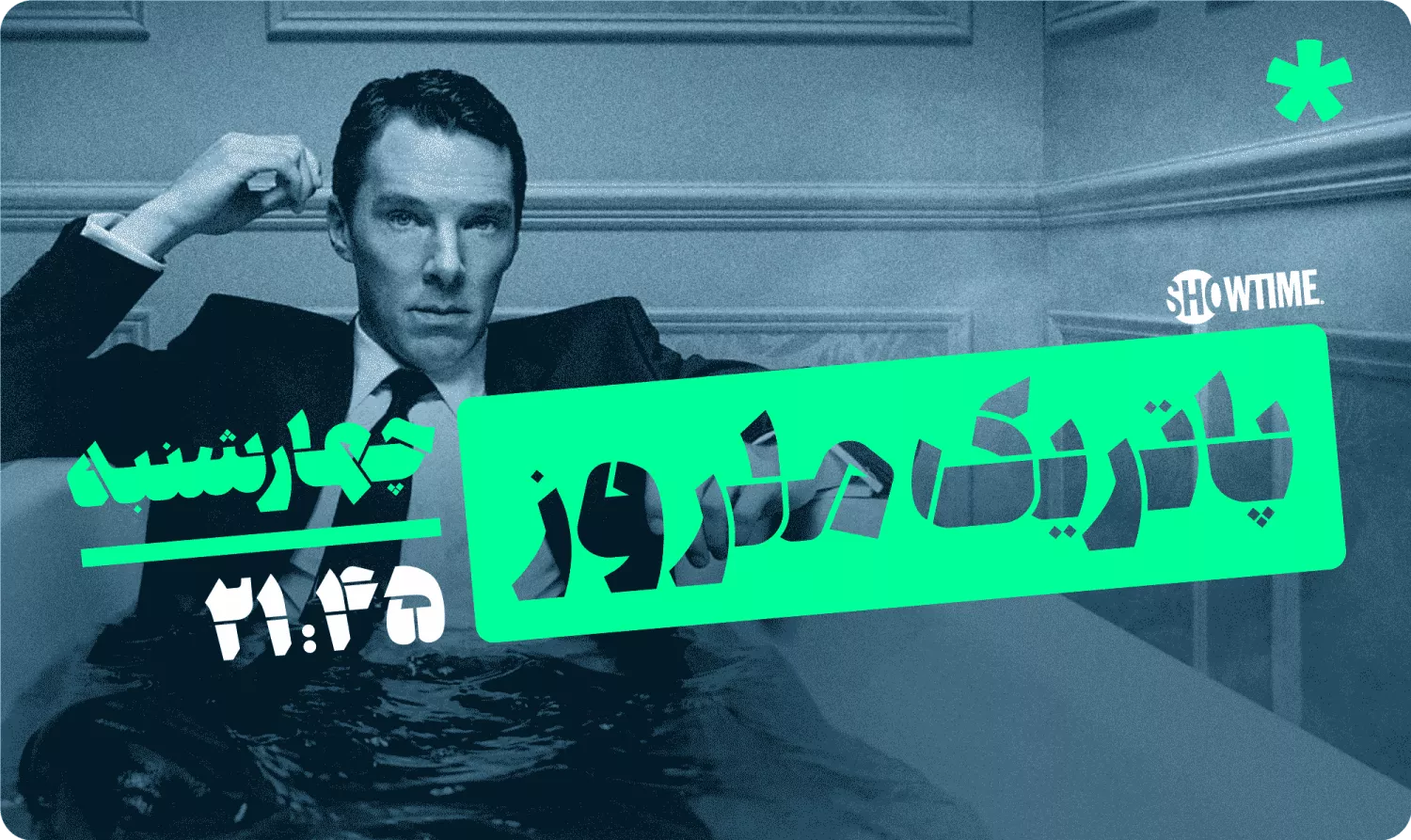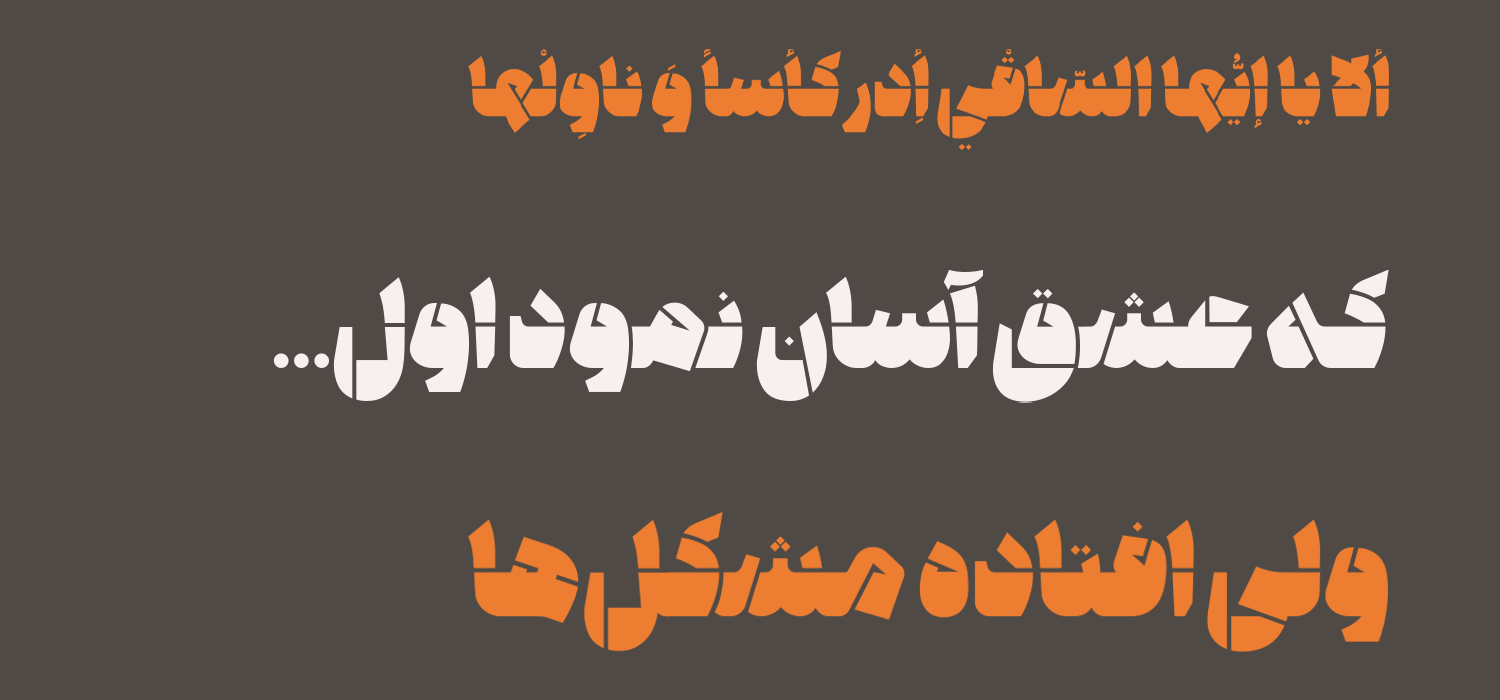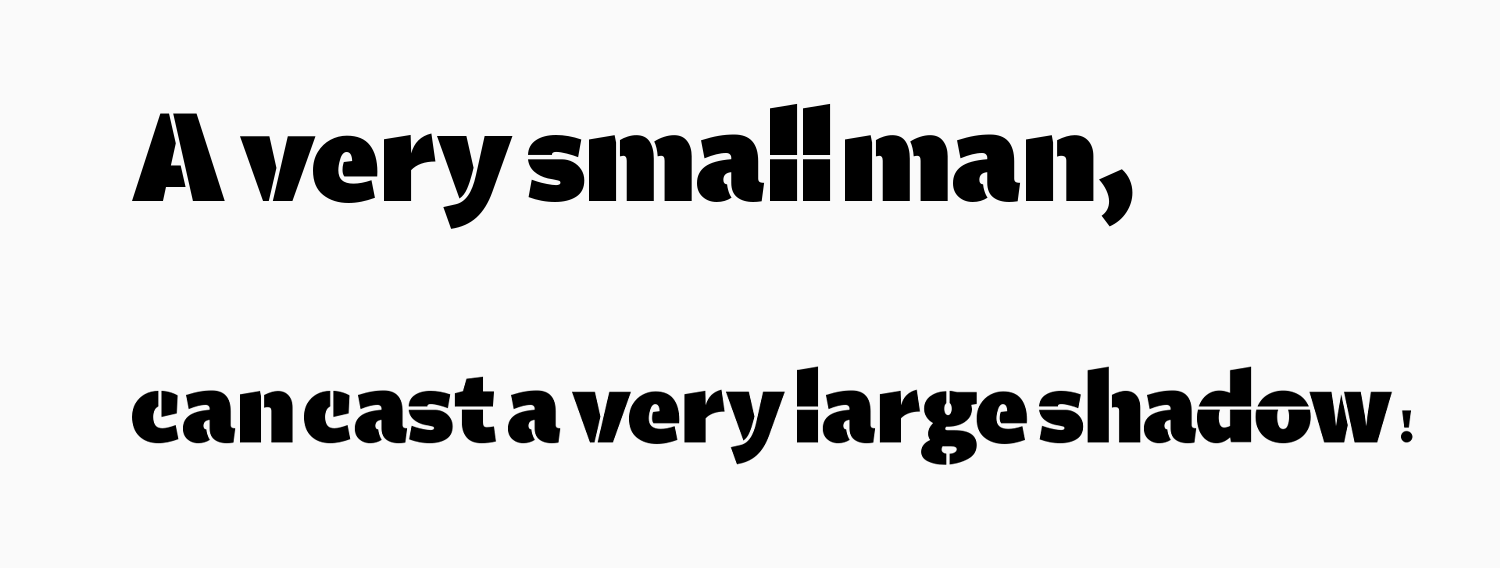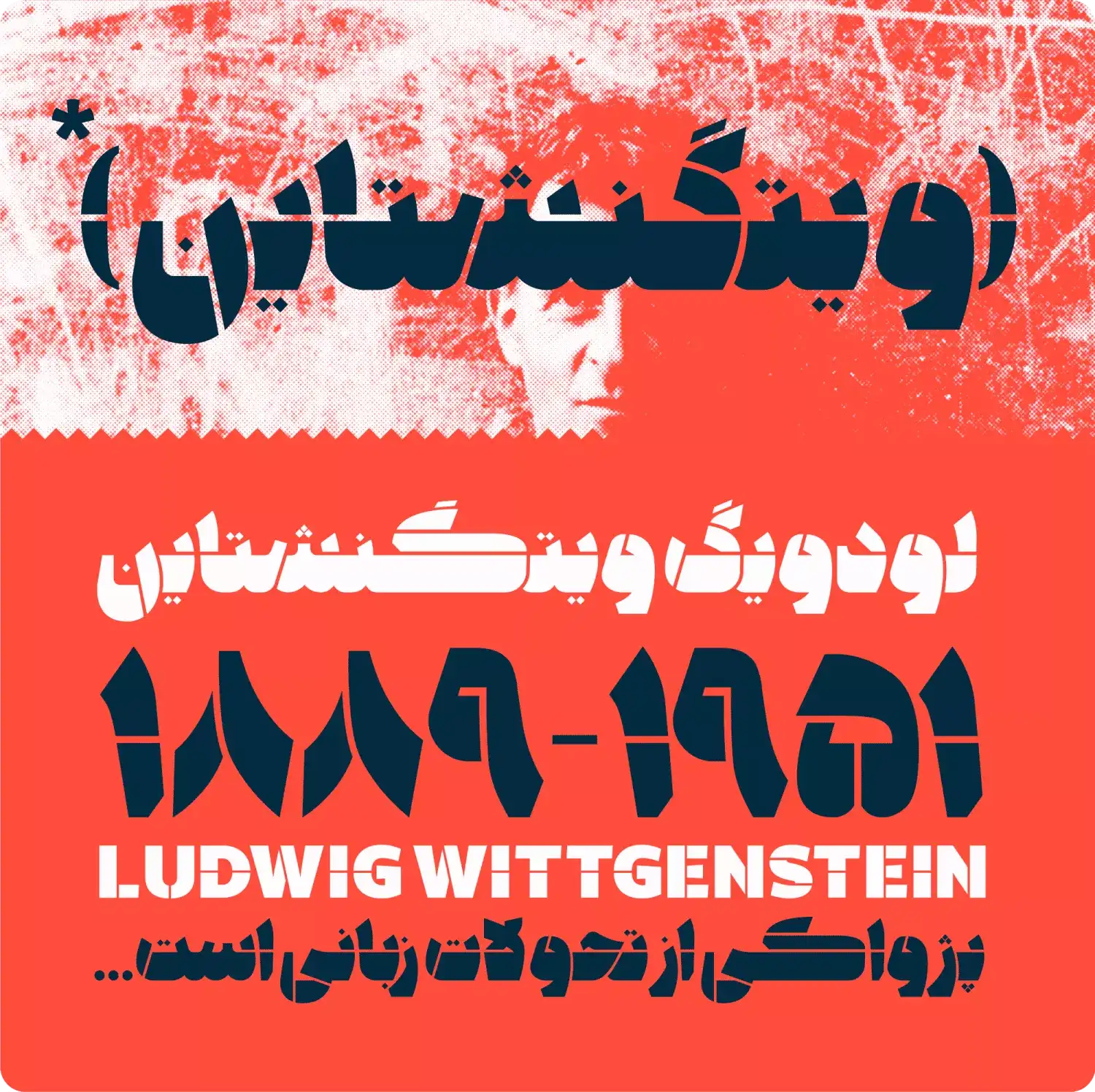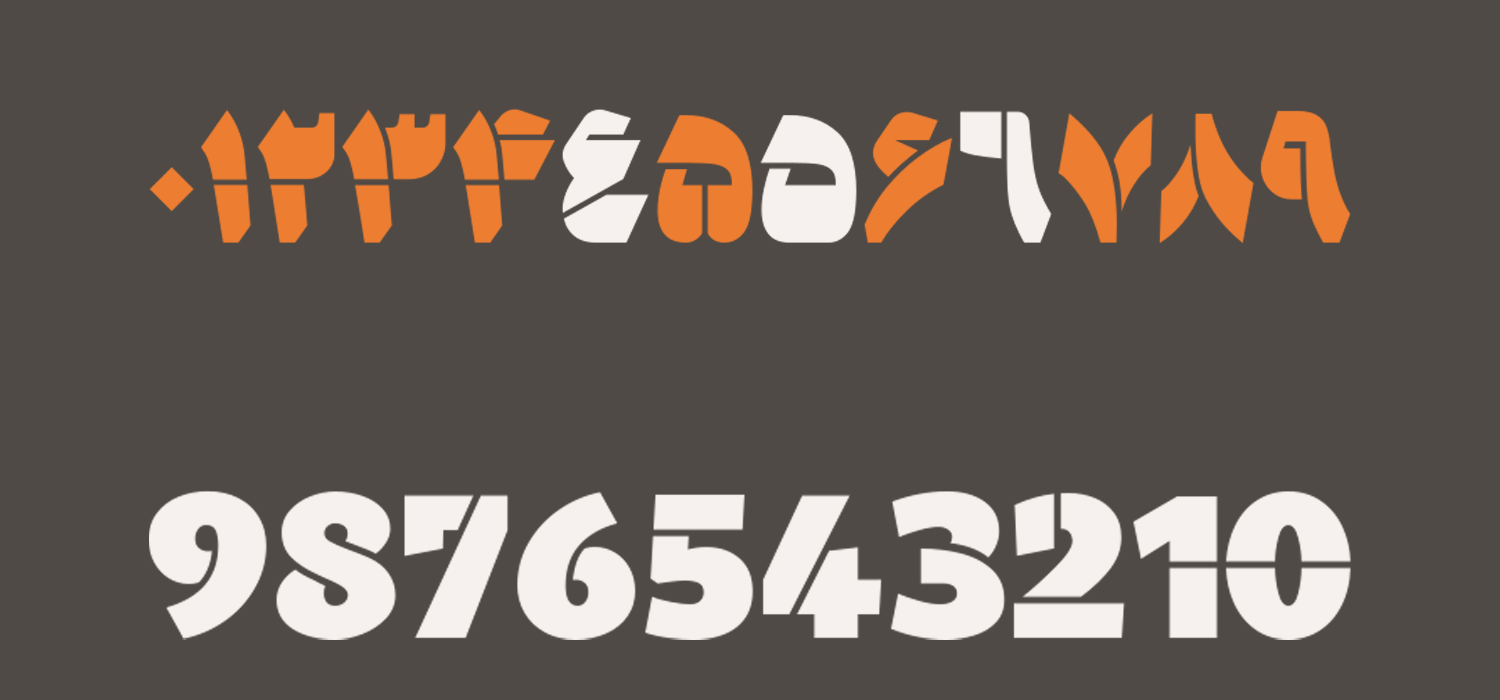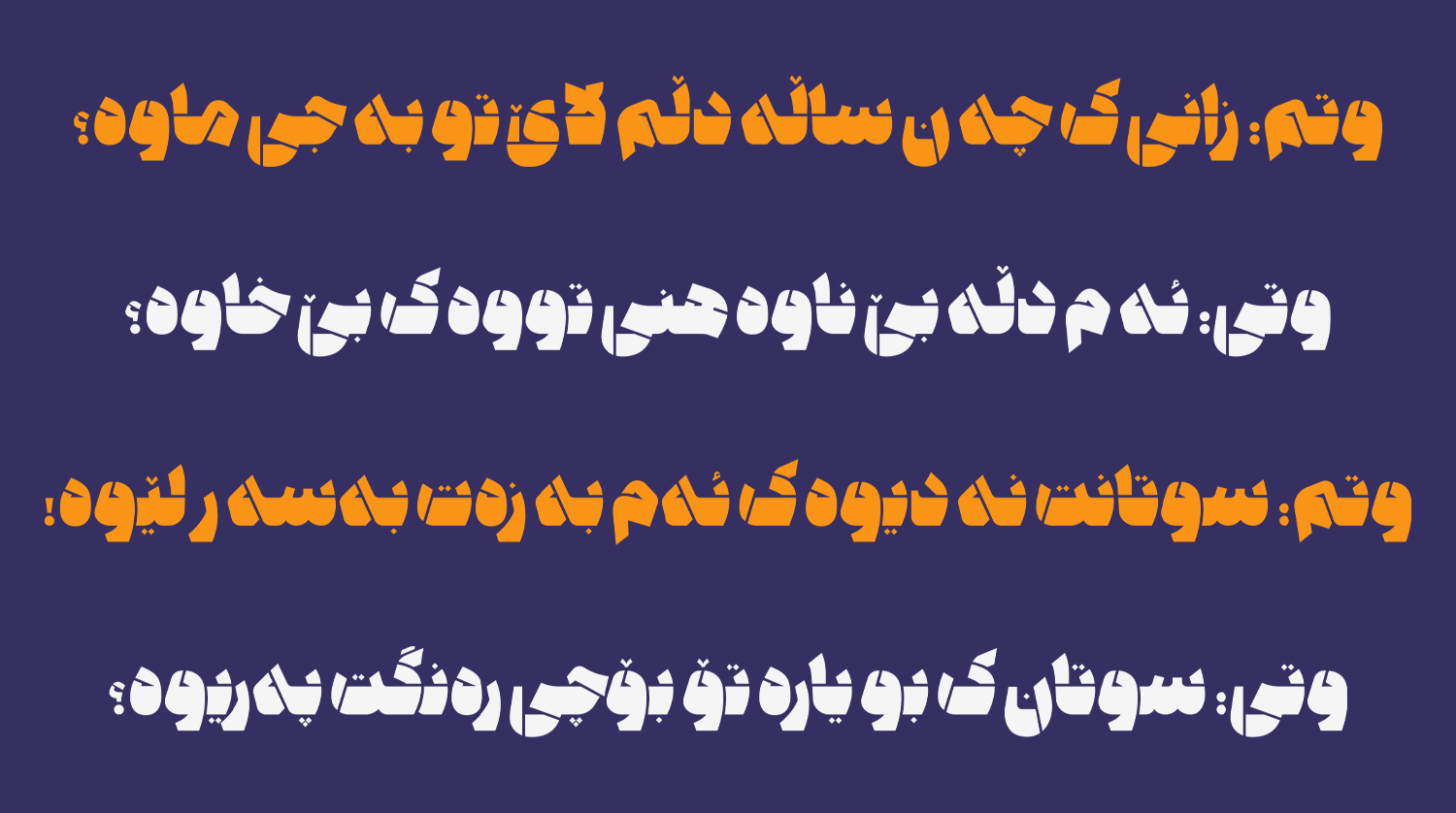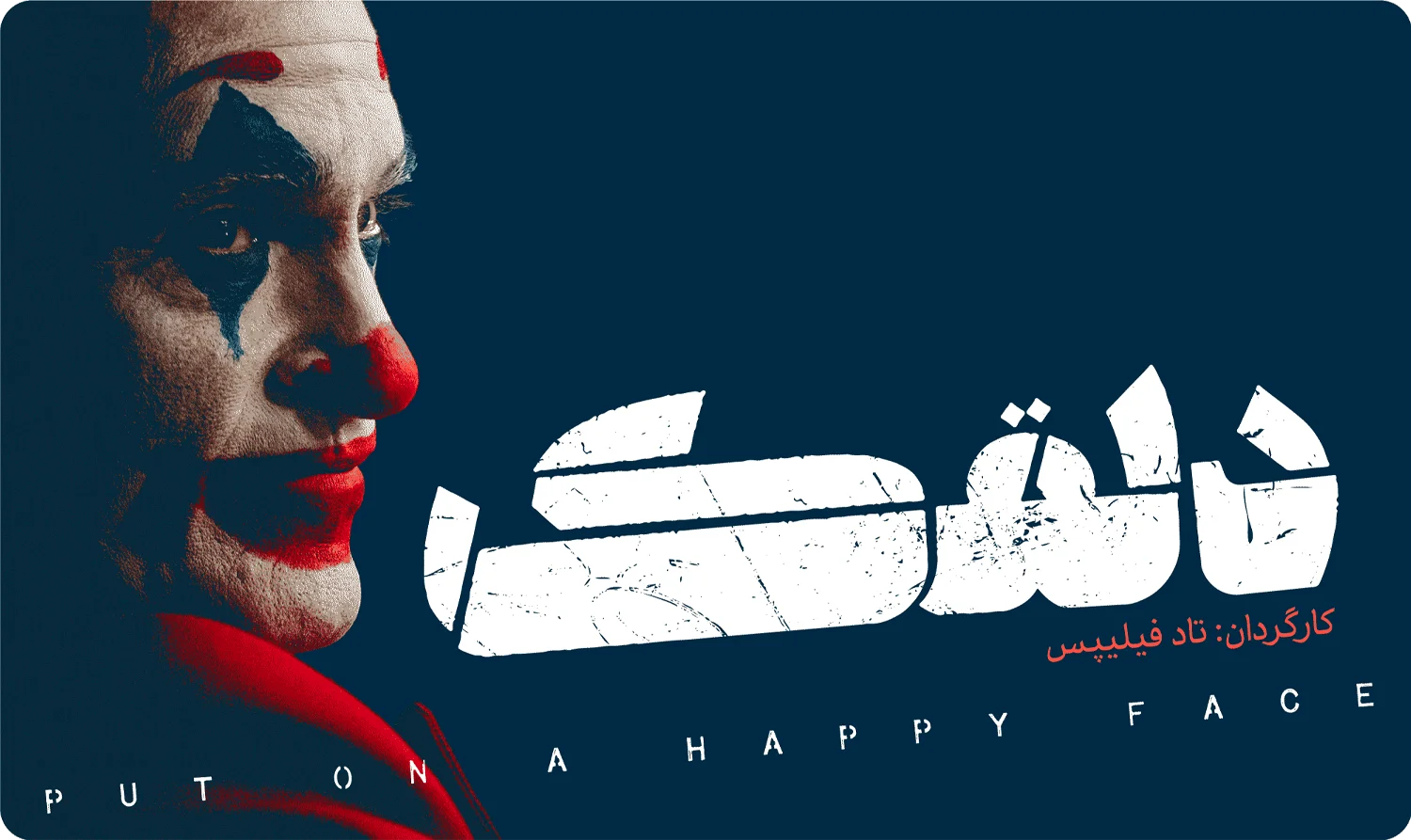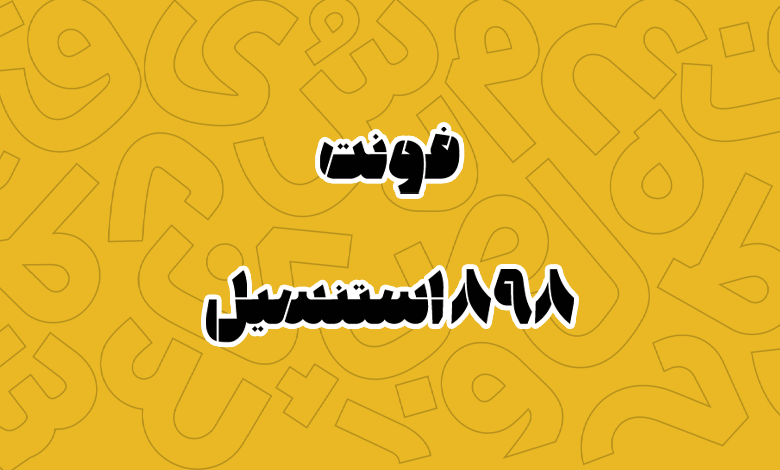
فونت ۸۹۸ استنسیل (۸۹۸ Stencil)
فونت ۸۹۸ استنسیل (به انگلیسی: 898Stencil) قلمی در گروه فونت عناوین است که با وزن سیاه و ضخیم یک فونت غولپیکر بهنظر میرسد. این فونت با برشهای استنسیلی بر پایه خط نسخ طراحی شده است که میتواند برای استفاده تبلیغاتی، مطبوعات و هر جایی که نیاز به قلمی با وزن سنگین و نمایشی داشته باشید عالی باشد.
این فونت توسط فریدون نعمت پور به منظور پر کردن خلا فونت چاق فارسی با این سبک خاص استنسیلی طراحی شده است که صرفا دارای یک وزن سیاه (Black) است. توسعه این قلم را به فرمت دیجیتال و نرمافزاری کامیاب جعفری انجام داده است.
در ادامه این نوشته از سایت فونتچی به نقد و بررسی کامل فونت ۸۹۸ استنسیل خواهیم پرداخت؛ قلمی که از امکانات مختلفی همچون اعداد فارسی، استفاده از اعراب و کاراکترهای کوچکتر نسبت به حروف و ساختار جدا در تمامی بخشهای هر کاراکتر یک فونت نمایشی عالی است.
برای آشنایی با سبک استنسیل کافی است نگاهی به شعارنویسی روی دیوارها یا تبلیغات اینچنینی که از طریق اسپری رنگ صورت میگیرد نگاهی بیندازید. خطوطی که وظیفه نگهداری زمینه چاپ، خصوصا برای حروفی که جدا شونده هستند را دارد همان سبک استنسیل را تعریف میکنند.
در زبان فارسی جای یک فونت استنسیل خالی بود و طراحان مجبور بودند تا با استفاده از روشهایی که در نرمافزارهای گرافیکی وجود داشت، این خطوط را روی حروف ایجاد کنند. به همین جهت فونت استنسیل ضمن اینکه چنین نیازی را پوشش میدهد، برای استفاده تبلیغاتی و عناوین طراحی شد. فونت تیتر گرافیتی استنسیل اولین فونتی است که با چنین سبکی برای زبان فارسی طراحی شده است.
این قلم دارای ساختاری کاملا نمایشی است که وجود سبک استنسیل به دلیل نوع استفاده ای که در طول این سالها در ایران برای شعارنویسی داشته است، موجب جلب توجه بیشتر خواهد شد.
سبک طراحی و وزن فونت ۸۹۸ استنسیل
فونت استنسیل ۸۹۸ صرفا از یک وزن سیاه (Black) پشتیبانی میکند. هدف این بوده فونتی کاملا چاق (FAT) در اختیار طراحان قرار گیرد تا از آن برای عناوین استفاده نمایند. این قلم برای متون طولانی مناسب نبوده و میتوانید برای جملات کوتاه و عناوین از آن استفاده کنید.
وجود فضاهای خالی که در زوایای مختلفی در تمامی حروف و اعداد این فونت وجود دارد، حرکت و پویایی خاص خود را به این قلم داده که موجب درگیر کردن چشم میشود. مهمتر از همه اینکه ثابت نبودن زاویه این خطوط، موجب ایجاد بازیگوشی در قلم و جلب توجه بیشتر شده است.
پشتیبانی کامل از ۶ زبان متنوع
فونت استنسیلی فارسی ۸۹۸ یک قلم چند زبانه است که علاوه بر زبانهایی که بر اساس رسم خط فارسی همچون کردی، عربی و اردو هستند، از زبانهای لاتین انگلیسی و فرانسوی نیز پشتیبانی کامل و استانداردی دارد.
در نسخههای خاورمیانهای تمامی حروف، اعراب، کاراکترهای خاص و تزئینی تا جایی که مشترک هستند در قلم پیادهسازی شده است و برای حالتی هم که صفحه کلید روی زبان خاصی غیر از فارسی قرار دارد که حروف آن زبان متفاوت است، گلیف اختصاصی پیاده سازی شده است.
برای نمونه حروف «ک، ی، ه، ؤ، ئ» در زبان عربی و حروف «ﮧ، ﮩ، ے» در زبان اردو که متفاوت از نسخه فارسی هستند پیادهسازی شده است. برای زبانهای لاتین همچون حروف «ç, ü» در زبان فرانسه که متفاوت از نسخه انگلیسی هستند نیز این حروف پیاده سازی شده است.
برای زبانهای لاتین انگلیسی این قلم از فونت (Tabac sans (Tomas Brousil استفاده شده است که بهجز برشهای استنسیلی هیچ تغییر دیگری در آن صورت نگرفته است.
فونت لاتین استنسیل ۸۹۸ یک تفاوت عمده با سایر فونتهایی که تاکنون معرفی کردیم دارد؛ علاوه بر پشتیبانی زبان انگلیسی، این قلم پشتیبانی کاملی از زبان فرانسه داشته و تمامی حروف مختص این زبان را با همان سبک خط خورده استنسیلی پشتیبانی میکند.
نکتهی دیگر اینکه با توجه به اینکه زبان ترکی استانبولی نیز حروف خود را از زبانهای انگلیسی و در تعدادی حروف از زبان فرانسه وام گرفته است، برای این زبان نیز امکان استفاده از این قلم را تا حدودی خواهید داشت.
دارای حروف جایگزین متنوع
ویژگی دیگر فونت استنسیل ۸۹۸ پشتیبانی از ترکیبات و حروف جایگزین است که امکان تایپ کلمات به شکلهای متفاوتی را به شما خواهد داد.
همانطور که در تصویر زیر میبینید، ترکیبات و حروفی مثل «ک، گ، لا» دارای شکل متفاوتی از نظر تایپ هستند. این مورد برای استفاده در عناوین میتواند روی توجه مخاطب تاثیر بگذارد؛ خصوصا در جملات کوتاه که با نشان دادن یک بی نظمی و ظاهر متفاوت از نظر حروف، باید تمرکز مخاطب روی خواندن خواهد شد.
حروف جایگزین فونت ۸۹۸ استنسیل محدود به موارد ذکر شده نبوده و باقی موارد را میتوانید به کمک راهنمای pdf موجود در بسته دانلود فونت ۸۹۸ استنسیل مشاهده کنید که راهنمای استفاده از آنها نیز درج شده است.
پشتیبانی حرفه ای از اعداد فارسی و عربی
فونت ۸۹۸ استنسیل از تمامی اعداد فارسی، عربی و لاتین متناسب با نوع زبان صفحه کلید پشتیبانی میکند و نگرانی بابت درج اعداد فارسی در زبان عربی را نخواهید داشت.
به عنوان نمونه اعداد «۴۵۶» عربی که متفاوت از اعداد «۴۵۶» فارسی هستند در این زبان به شکل استانداردی پیاده سازی شده است.
اما دو تفاوت عمده دیگر از نظر اعداد نیز در این قلم وجود دارد که در قالب فایل فونت جدا ایجاد شده و عبارتند از: